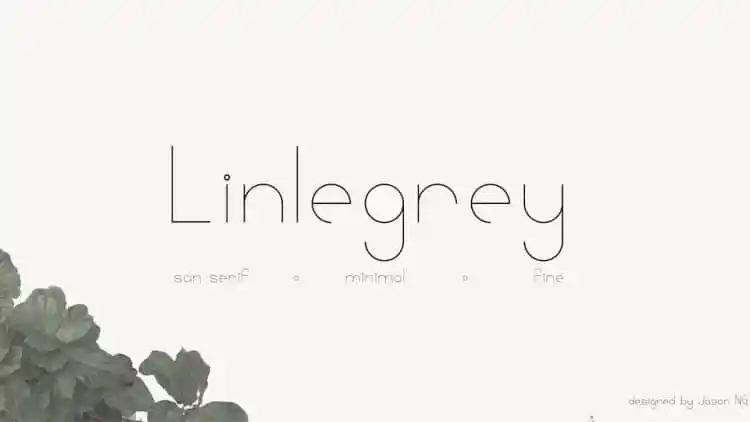
Linlegrey Sans Serif Font
Linlegrey Sans Serif é uma nova adição à família de fonts sans serif que traz consigo o espírito do avanço tecnológico. Inspirada nos desenhos pop cultural de construções de espaçonaves, essa font foi desenvolvida pelo designer 99designs conhecido como White Supply. Com um toque moderno e minimalista, Linlegrey é perfeitamente adequada para qualquer projeto de design que busque elegância fina. Sua simplicidade e clareza tornam-a uma escolha ótima tanto para marcas de marca quanto para logotipos. Além disso, seu charme moderno faz dela um ícone perfeito para blogs de estilo de vida digitais, onde sua presença pode destacar com eficácia. Numa era cada vez mais digitalizada e tecnológica, Linlegrey é uma opção que combina os elementos futuristas do design sem perder o toque elegante dos tempos atuais.